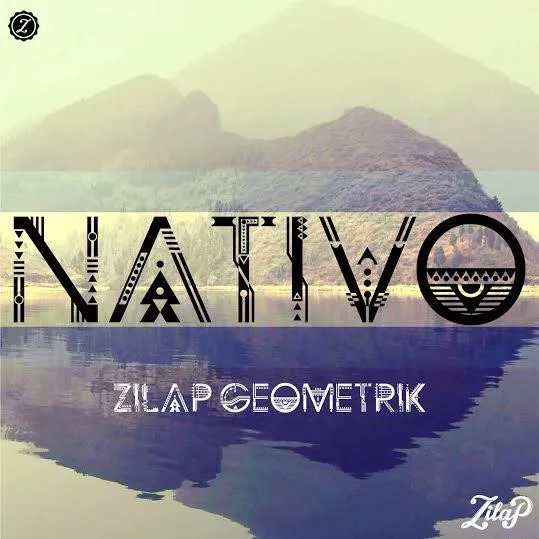
A fonte ‘ZILAP GEOMETRIK’ é uma criação elegante e sofisticada que oferece um toque moderno a qualquer projeto de design. Desenvolvida por Hamilton, essa fonte decorativa é perfeita para aqueles projetos que exigem um estilo único e arrojado. ZILAP GEOMETRIK traz linhas afiadas e formas geométricas que criam uma sensação de movimento e contemporaneidade. Seus traços são robustos, mas também têm o charme da simplicidade pura. Adaptable para textos simples ou complexos, ela oferece um toque moderno a qualquer projeto de design. Com apenas alguns cliques, você pode transformar suas ideias em algo realmente especial, seja uma assinatura elegante e minimalista, letras grandes para outdoor ou até mesmo um texto delicado para editoriais. Não importa o que você deseje projetar com ZILAP GEOMETRIK, Hamilton criou um instrumento poderoso que tornará seu trabalho de design ainda mais singular. Não se esqueça, para acessar todas as ferramentas e recursos adicionais da fonte ‘ZILAP GEOMETRIK’, simplesmente escreva  ou visite http://ljdesignstudios.es.tl.